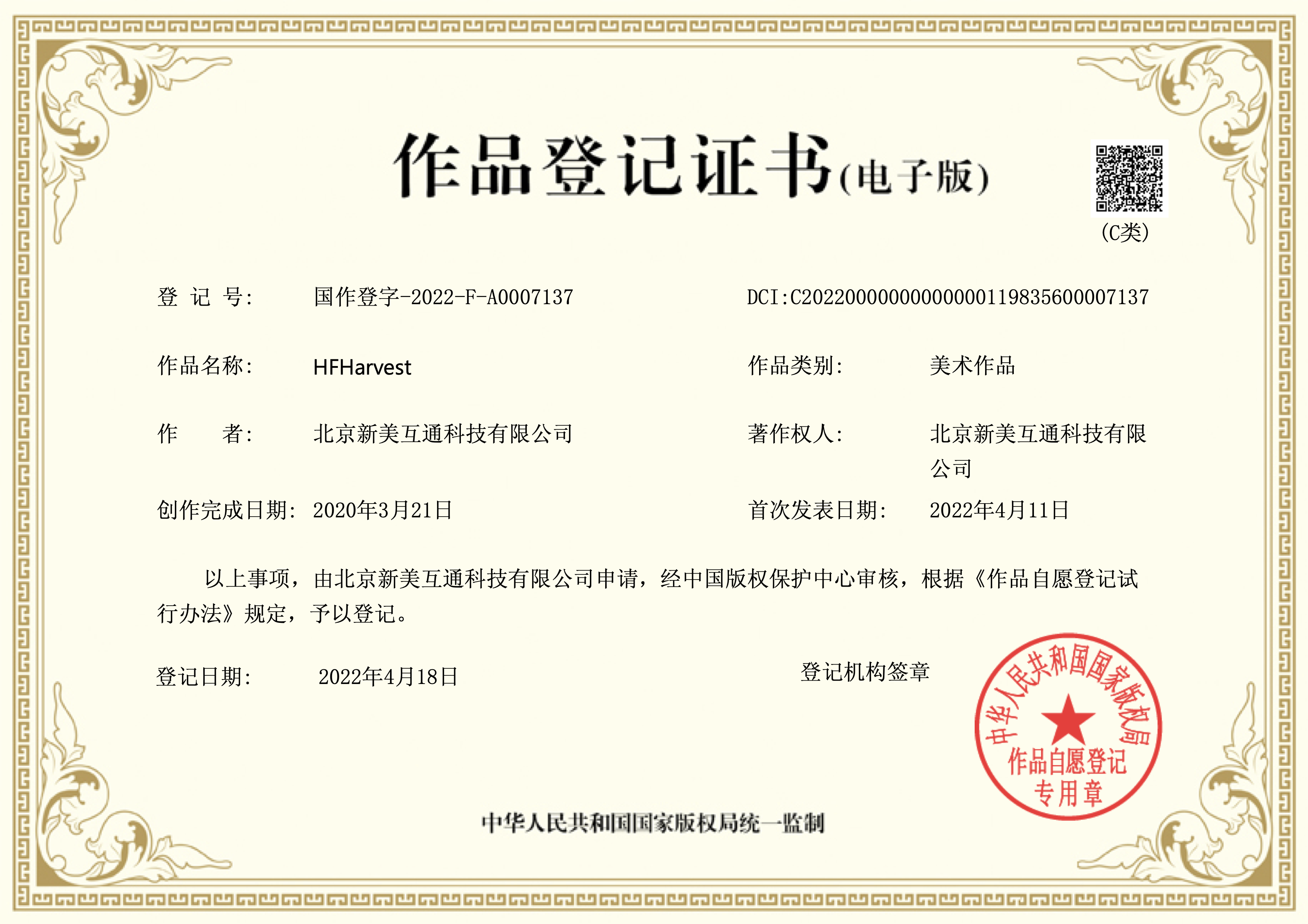
HFHarvest是一款圆润、温暖的无衬线字体,本字体可免费商用(请通过字谷网提交免费订单获取商用授权)。
不论是降低小写字高或是笔画斜切角的设计,各方面皆提升字体在各种载体上显示时的稳定性与易读性。不同于一般无衬线字体的几何圆形,HFHarvest方圆的字腔有如收成时饱满的果实,为整体字型增添了温暖、亲近的人文气息。